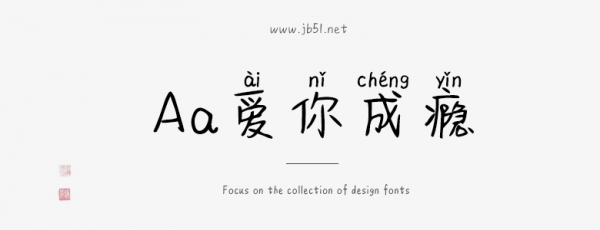
Aa愛你成癮是一款不錯(cuò)的藝術(shù)字體,由Aa字庫出品,字體筆觸略粗,書寫流暢 ,具有很好的視覺感,適合應(yīng)用于藝術(shù)設(shè)計(jì)、平面宣傳設(shè)計(jì)、網(wǎng)頁設(shè)計(jì),書法字帖等領(lǐng)域,需要的朋友可以前來本站下載。